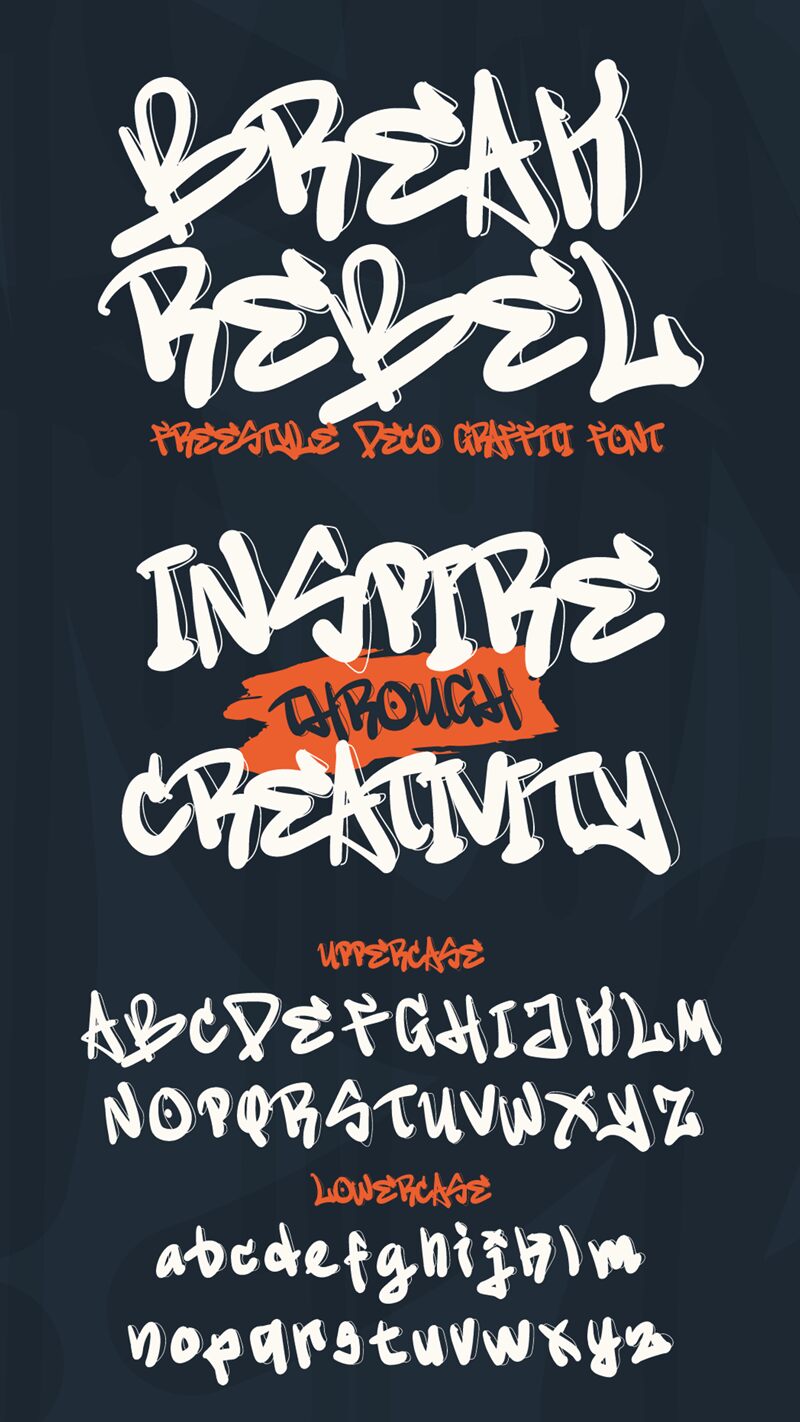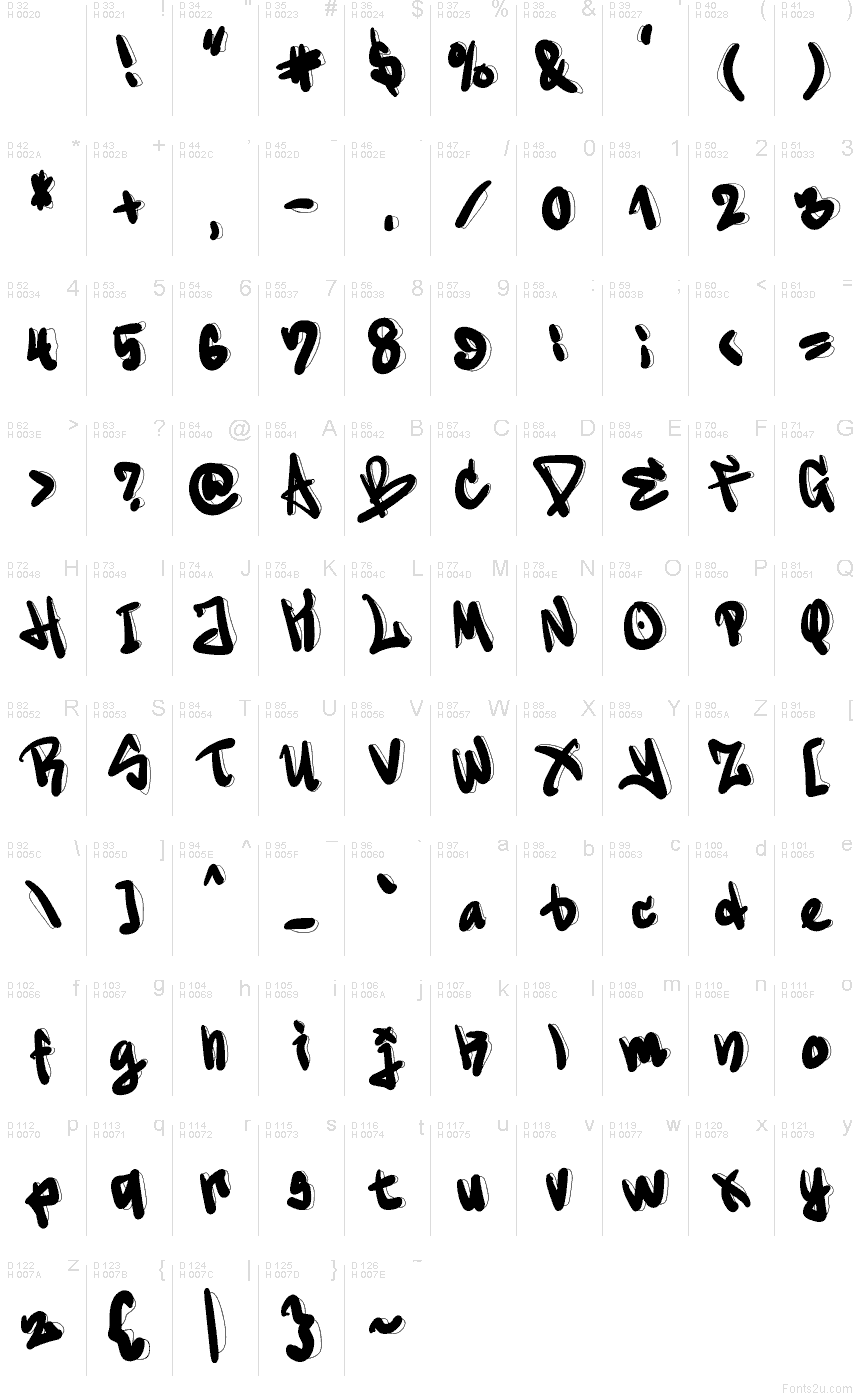
Písmo Break Rebel od Muhammada Panji Ramdhaniho ze studia Sipanji x Figuree útočí jako čerstvý markerový tag: je tučné, rychlé a nekompromisní. Tahy působí inkoustově a nabitě, s dynamickým švihem, který slovem projíždí jako neohrožený podpis. Je to bezplatné graffiti písmo, které si udržuje ten správný ruční rytmus, aniž by působilo chaoticky.
Break Rebel skvěle vynikne v logách pro streetwear, skejtových plakátech, hudebních obalech, náhledech videí na YouTube, letácích na akce, sadách nálepek a úderných nadpisech na sociálních sítích. Nastavte ho ve velké velikosti, aby textura štětce vynikla, a pro data a detaily ho zkombinujte s úzkým, neutrálním bezpatkovým písmem – nechte toto bezplatné písmo dělat ten rozruch, zatímco bezpatkové písmo zajistí čitelnost.